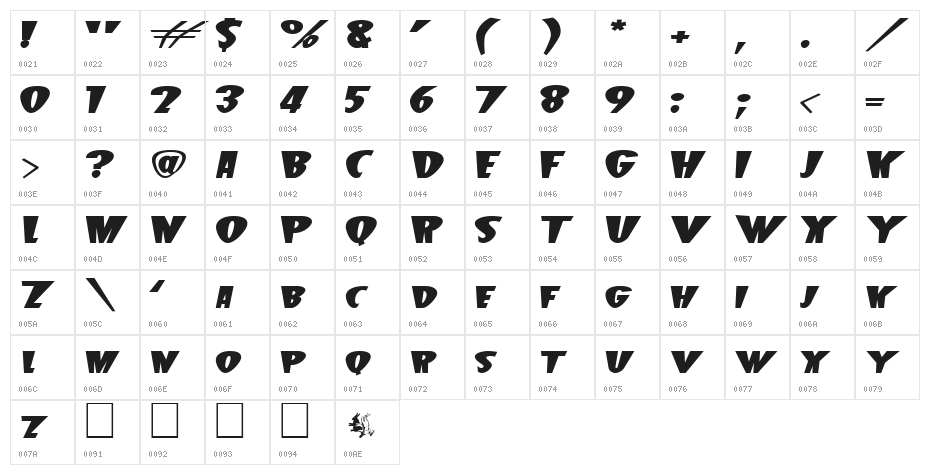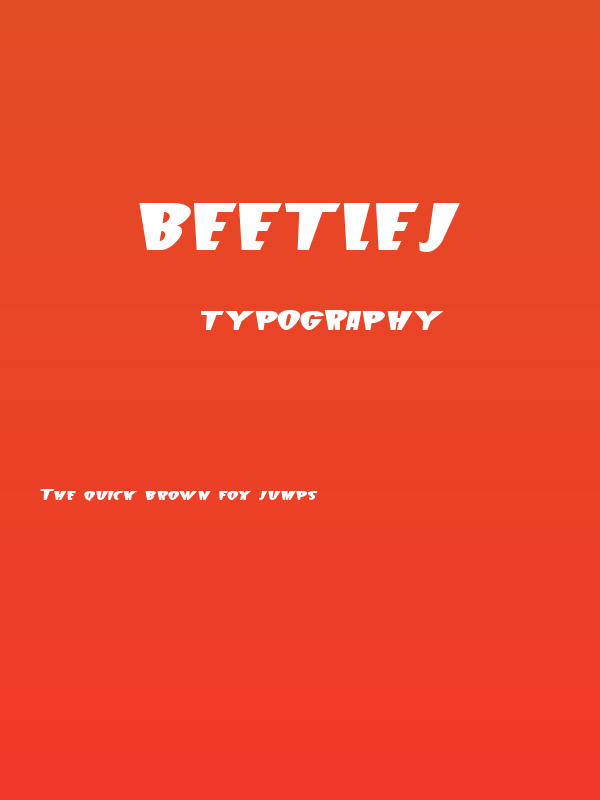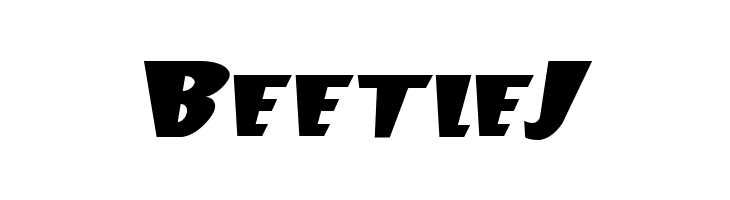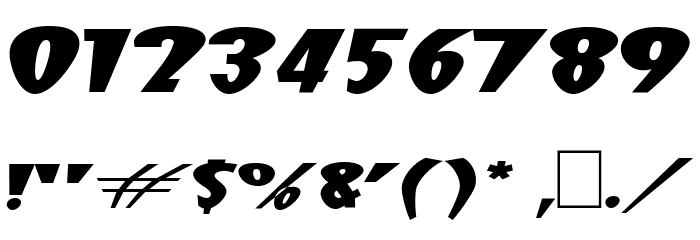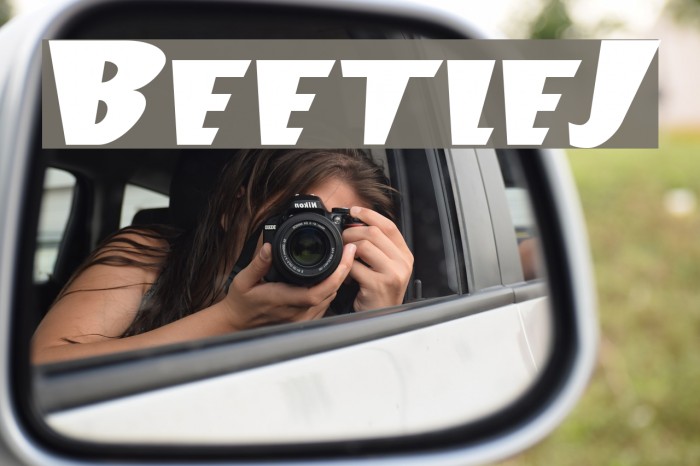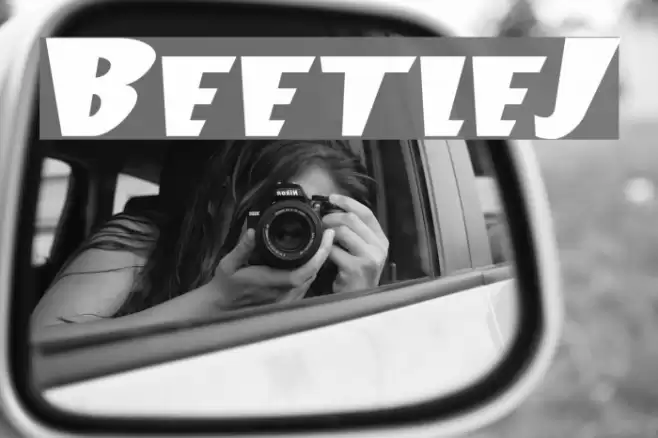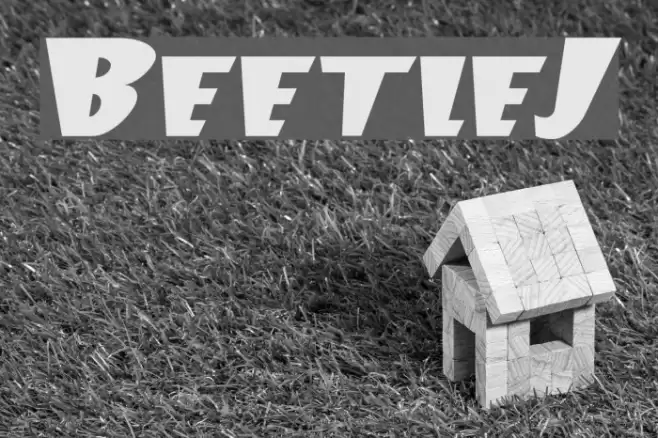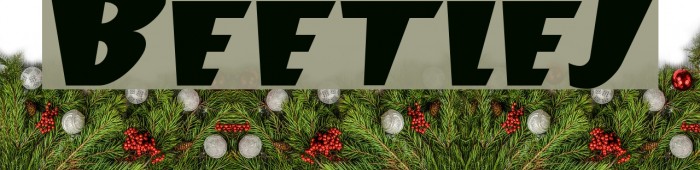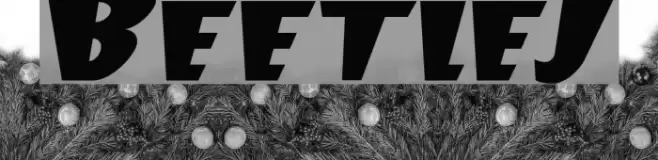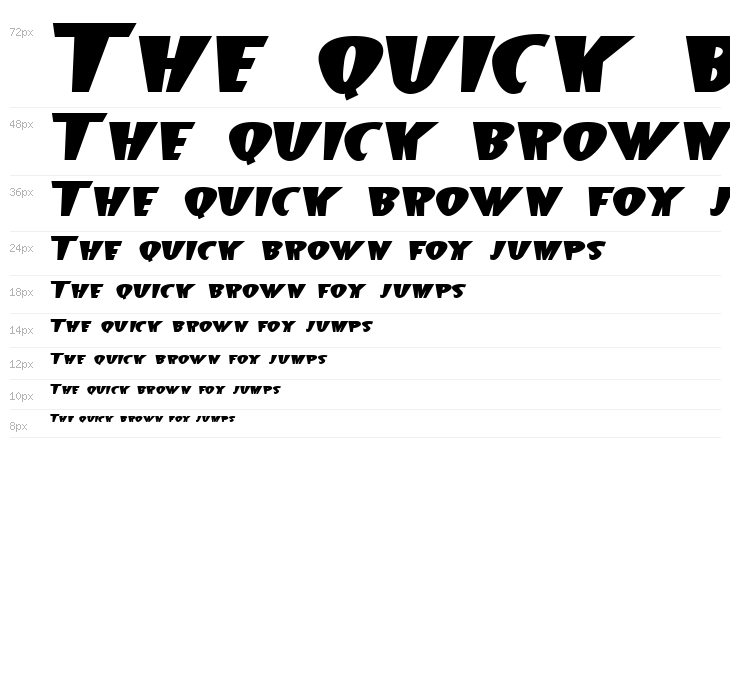
BeetleJ Font
| Projets proposés | Ideal for movie posters, video game titles, comic book covers, and any project needing a bold, eye-catching typeface. |